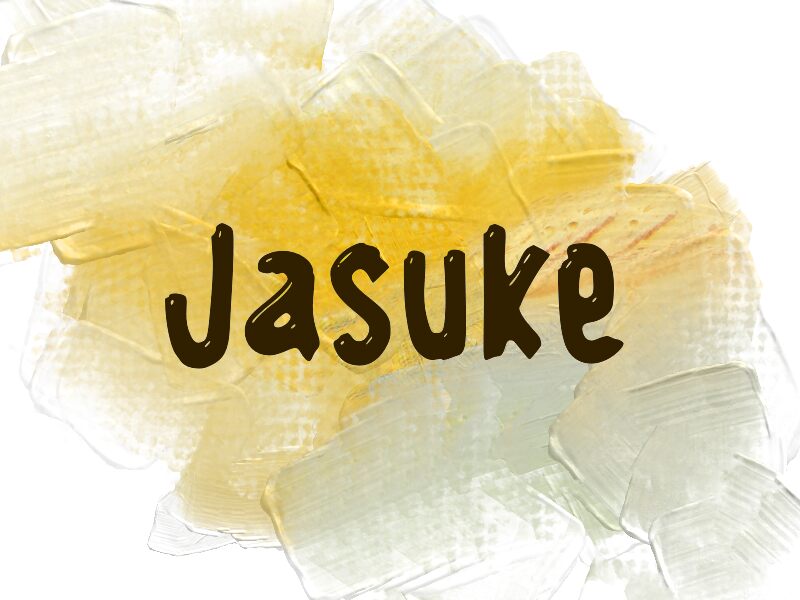
Jasuke от Wep — это бесплатный акцидентный шрифт (brush font) с игривым, «рукописным» характером. Буквы выглядят плотными и сочными, с закругленными штрихами, мягкими углами и легкой небрежностью в формах, что придает шрифту свободу, а не чрезмерную отточенность, — получается этакий уличный стиль с ноткой мультипликации.
Отлично подходит для заголовков плакатов, упаковок снеков, музыкальных флаеров, обложек видео на YouTube и повседневных брендов, где нужен бесплатный шрифт, который выделяется, не становясь при этом слишком строгим. Благодаря коротким, толстым и слегка приплюснутым формам, Jasuke лучше всего работает в коротких словах, заголовках и логотипах, где этот живой живописный ритм может проявить себя во всей красе.
Jasuke
Презентация и наглядный образец шрифта Jasuke